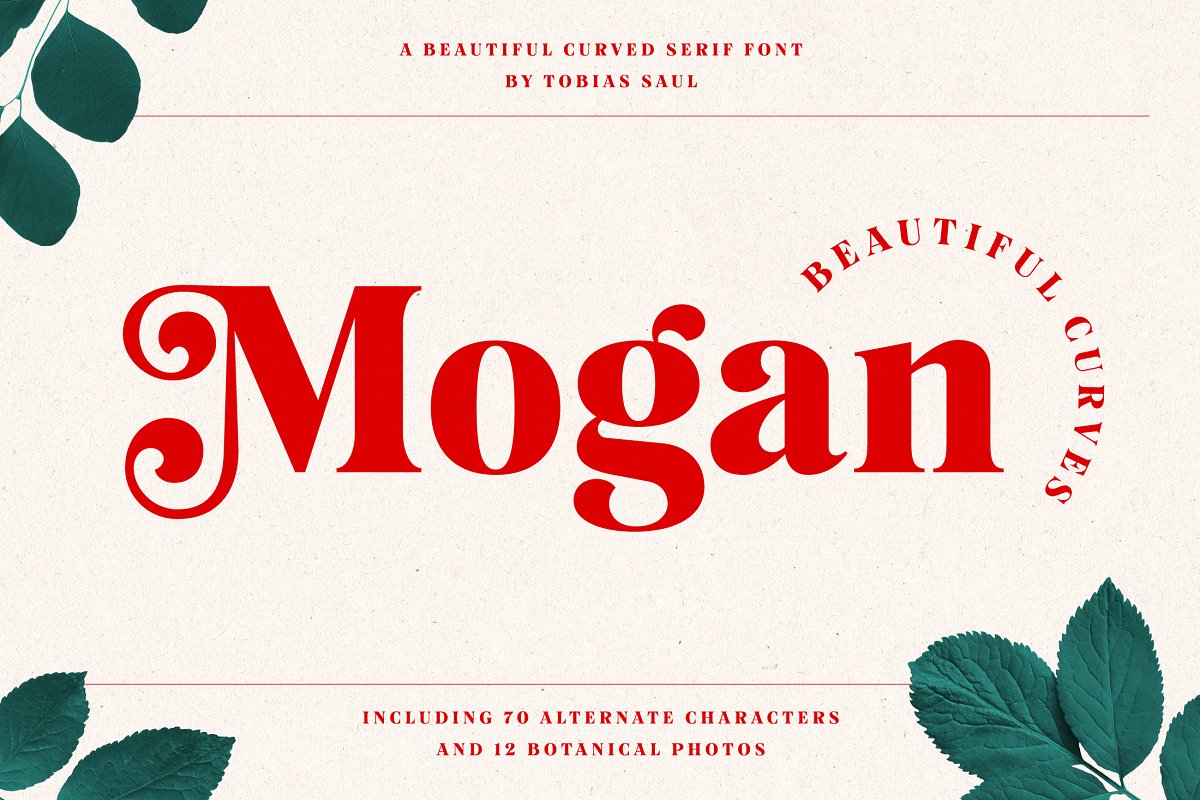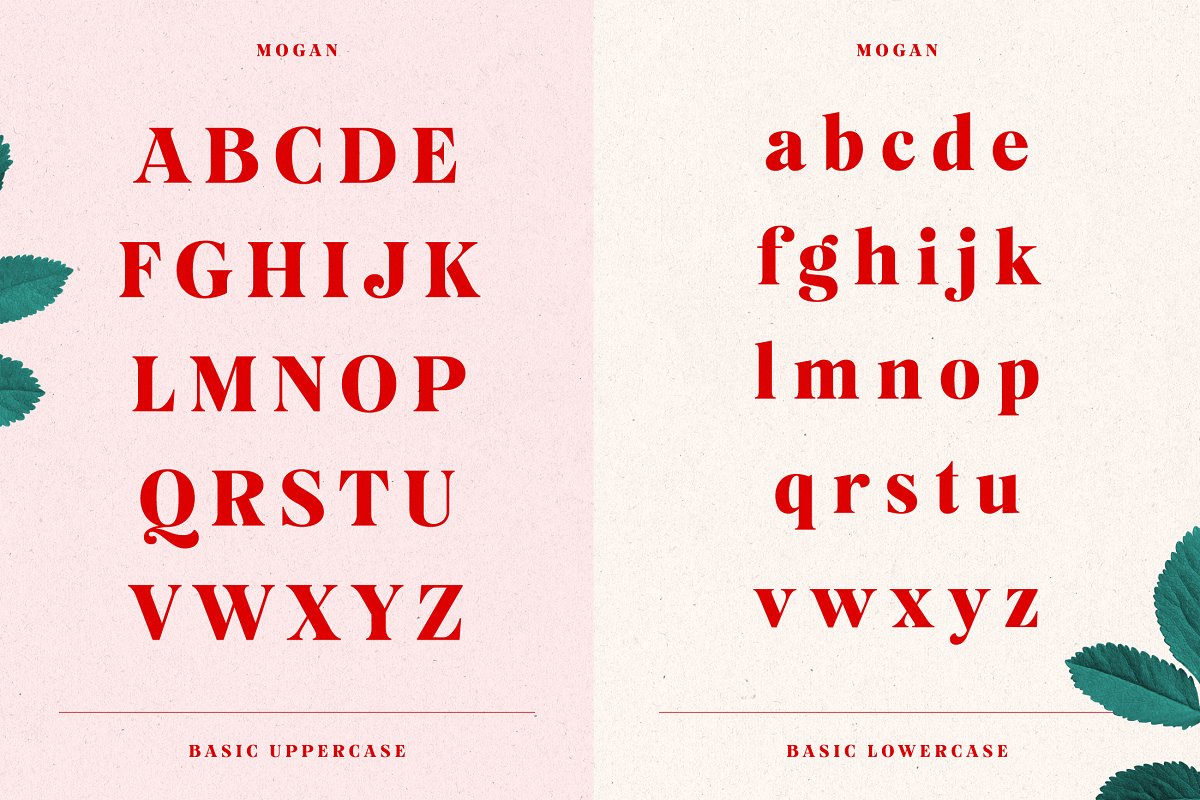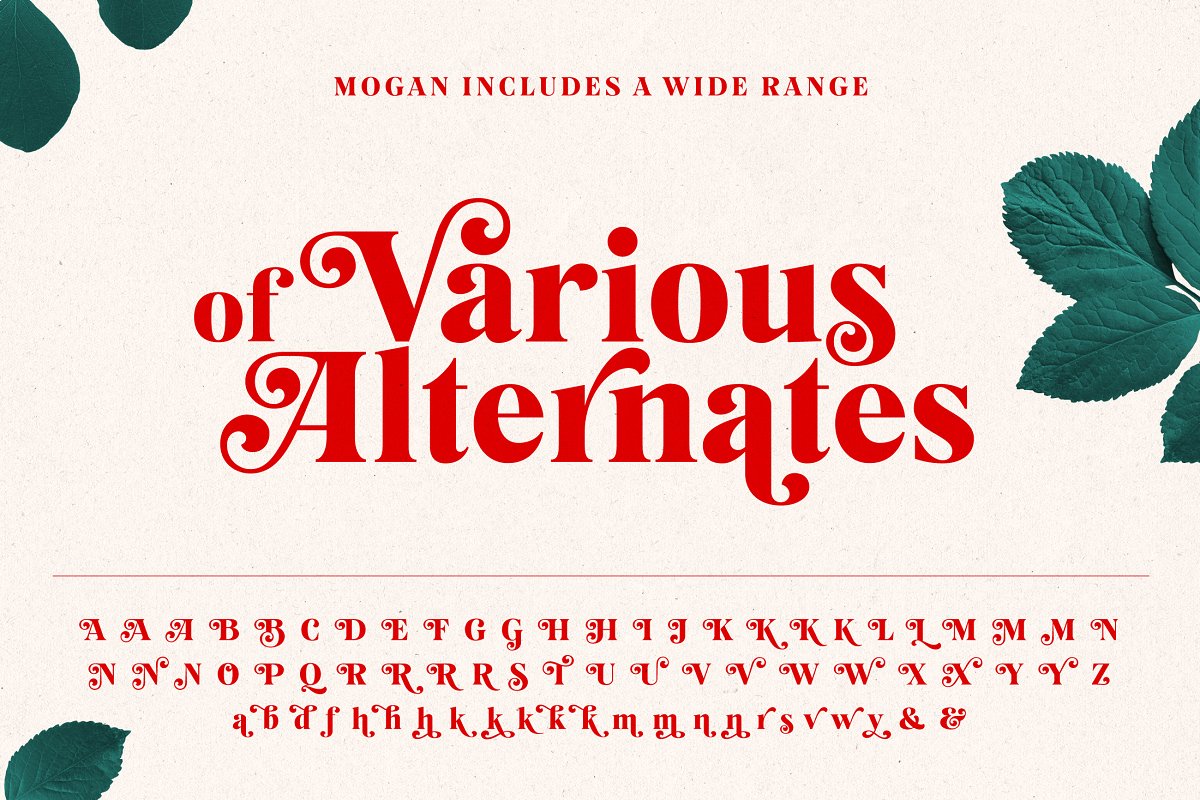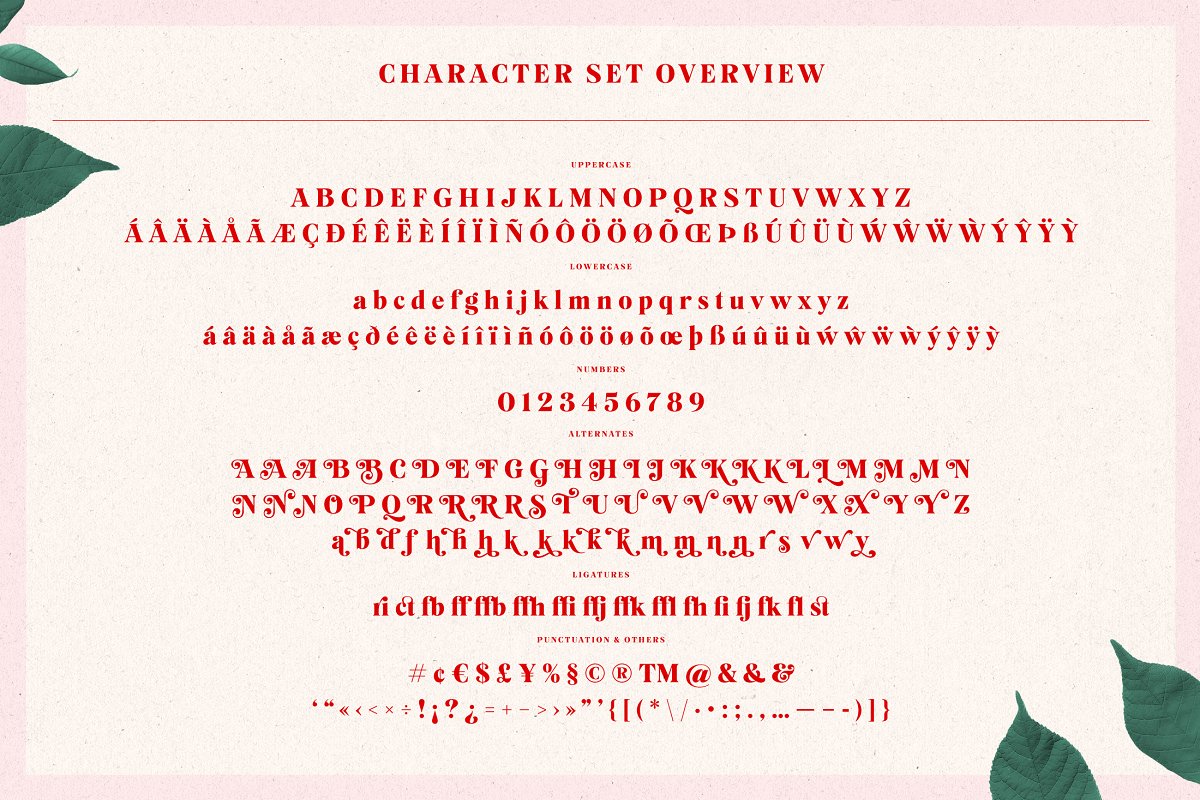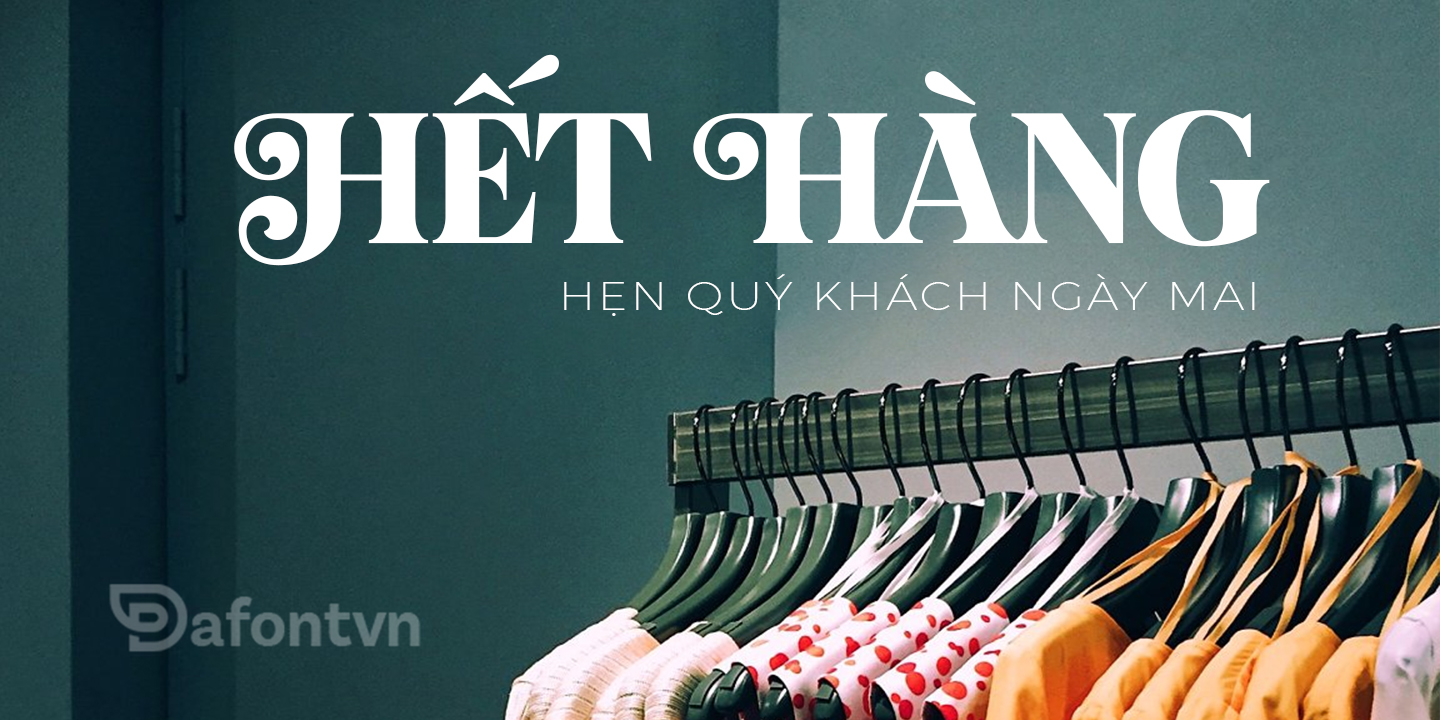
[Serif] Download Mogan Font tuyệt đẹp và ấn tượng
Mogan Font là dạng serif font với các đường nét độc đáo, có một vẻ ngoài hiện đại và mạnh mẽ. Với các thiết kế phong phú cho phép bạn có các tùy chọn thiết kế linh hoạt và hoạt động hoàn hảo cho các tiêu đề, logo, áp phích, bao bì, áo phông, bưu thiếp và nhiều hơn nữa.